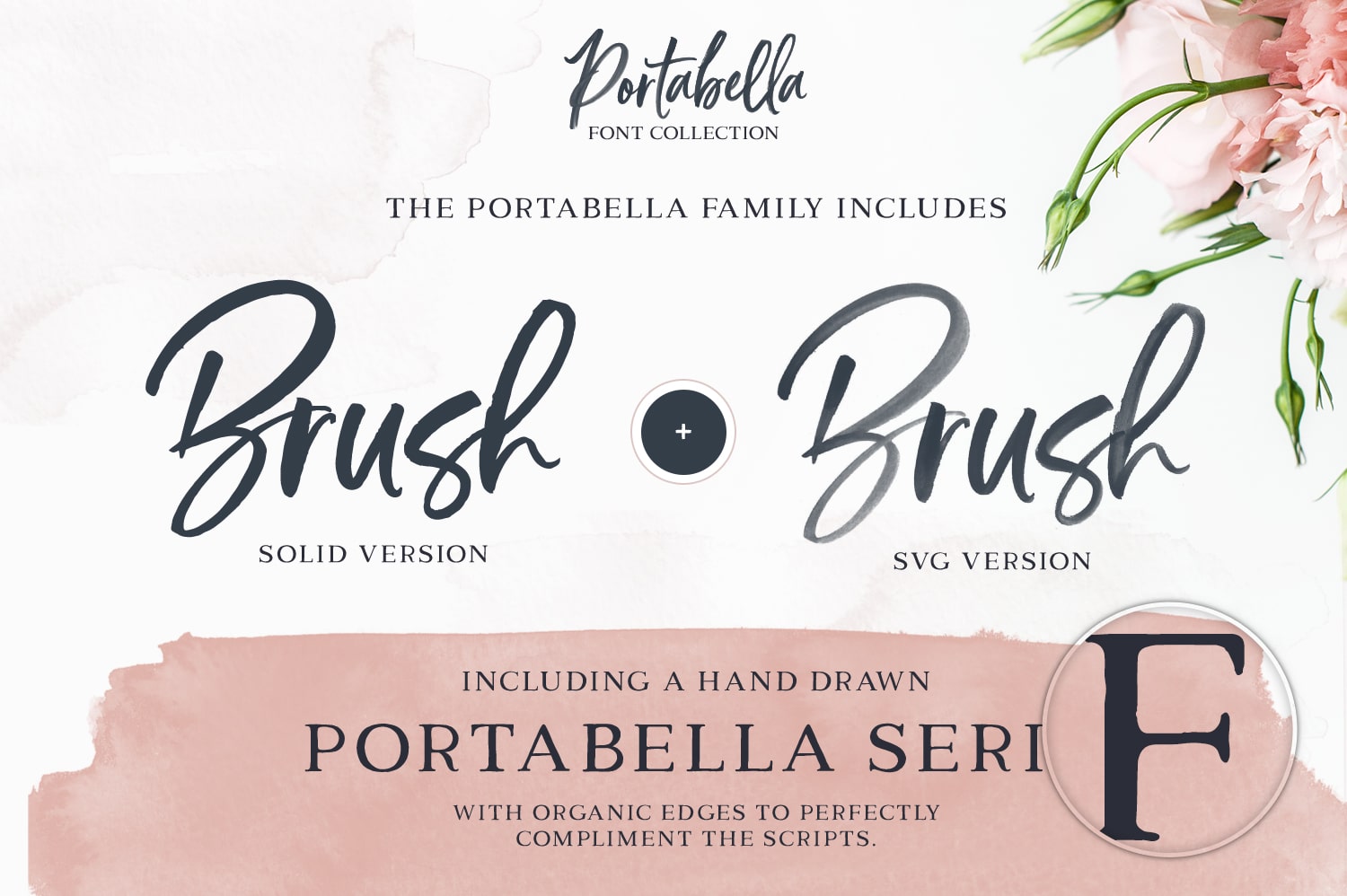
DESIGNCUTS(デザインカッツ)で、新しいバンドルが発売されました!
今回のバンドルは「デザイナーが愛用したい 極上フォントコレクション」。
「デザイナーが愛用したい 極上フォントコレクション」の気になる中身
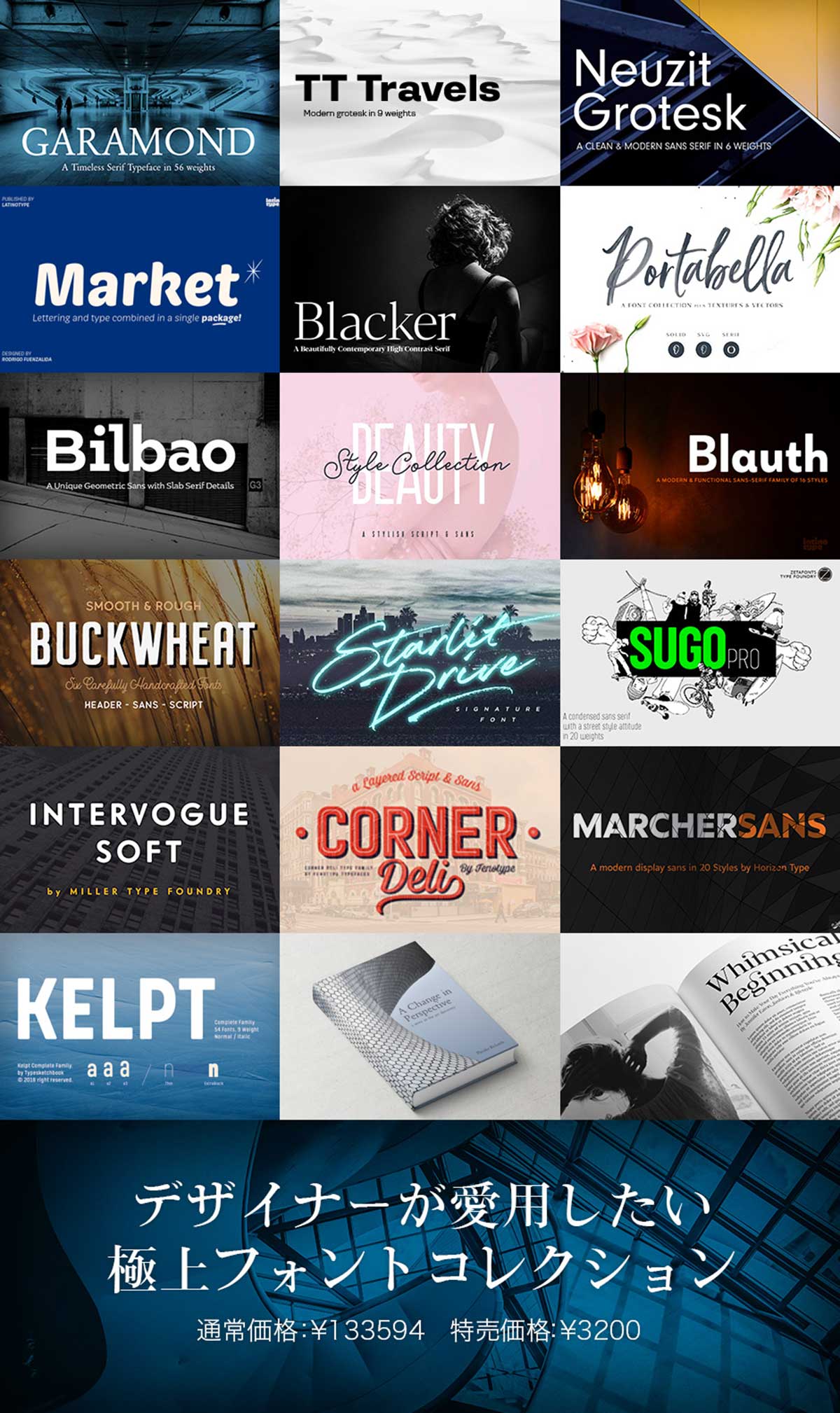
▼わたしが今回のバンドルで特に気になる素材はこちら!
持っておいて損なし!定番フォント:GARAMOND
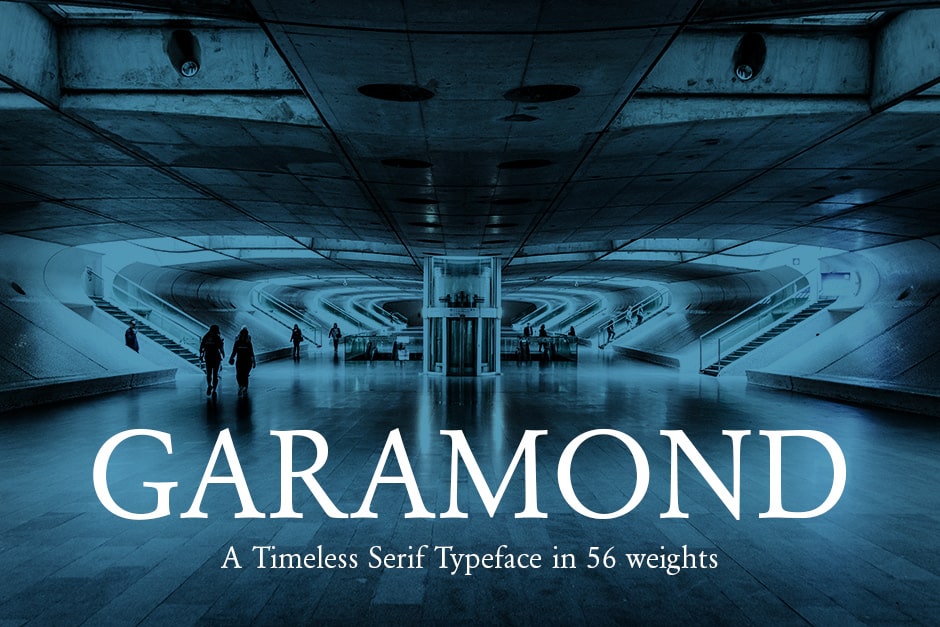
Claude Garamondによる伝説のフォントがなんと56ウェイトも収録。わたしも個人的に仕事でよく使っています。エレガントで読みやすく長文にも使えるので、ついつい選んでしまうフォントです。
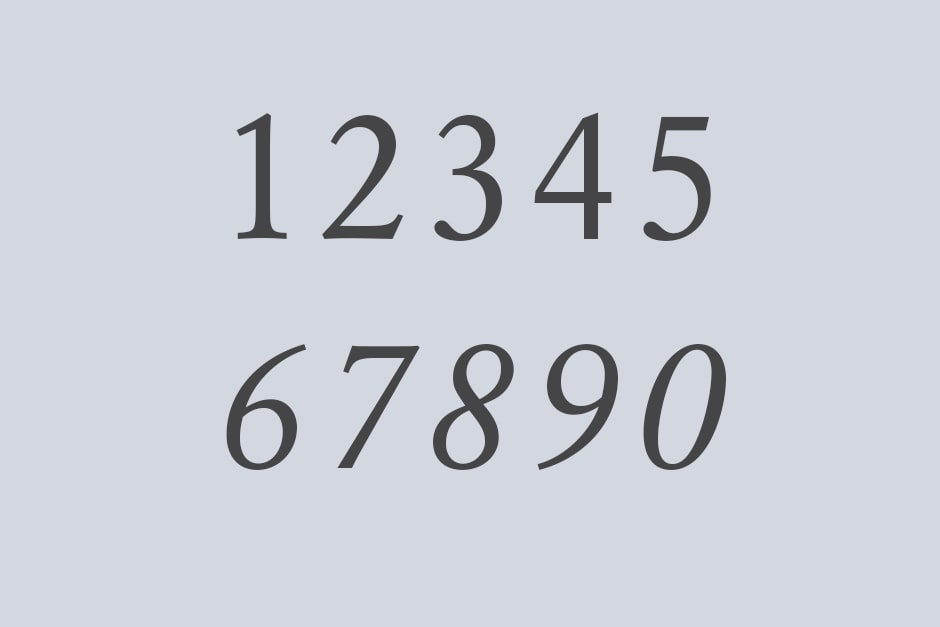
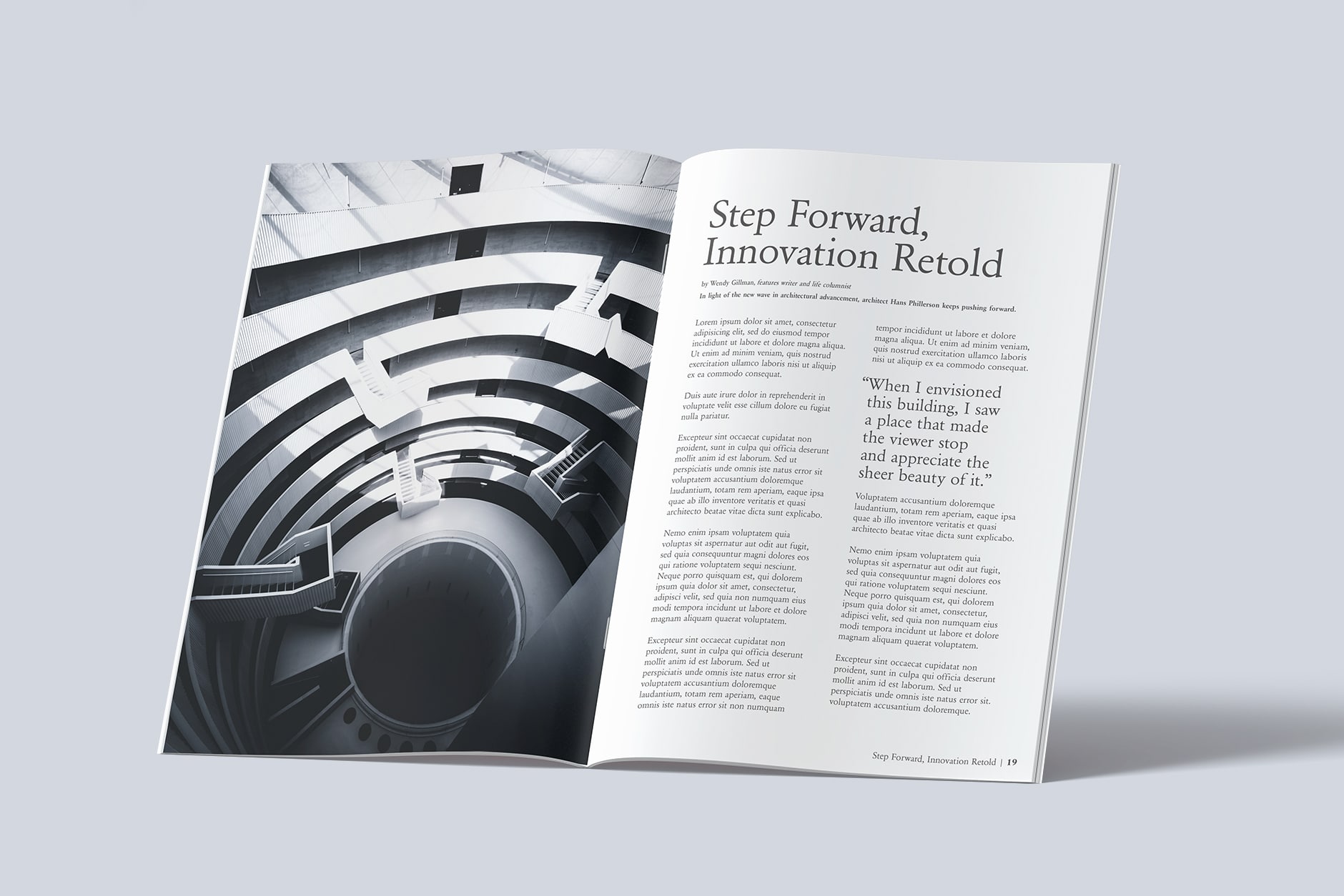
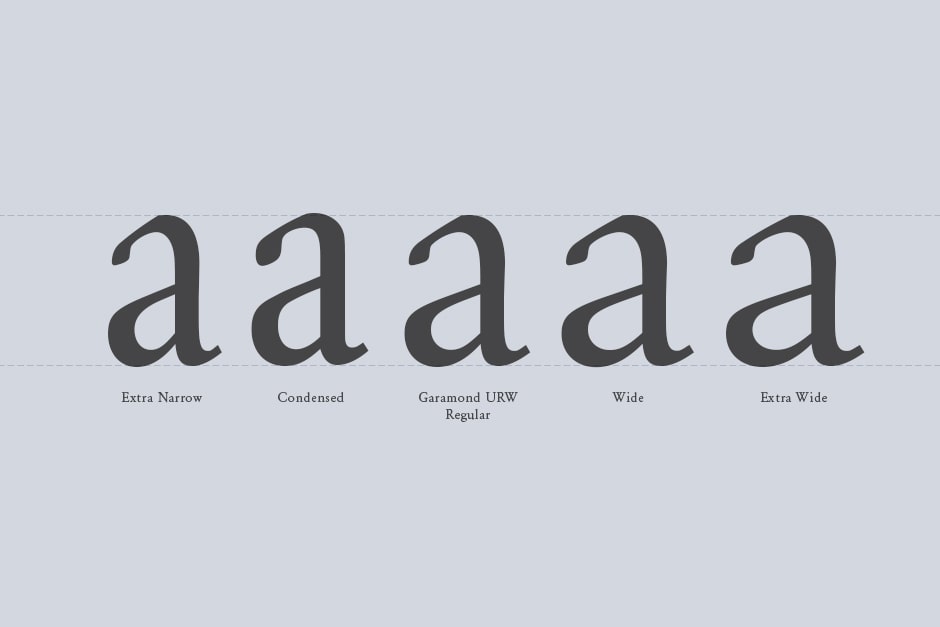
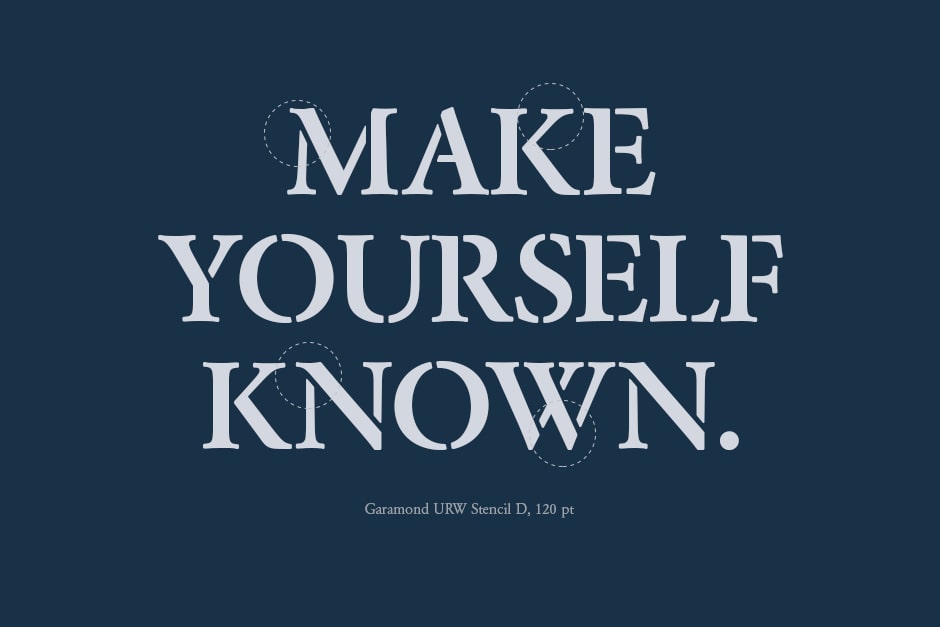
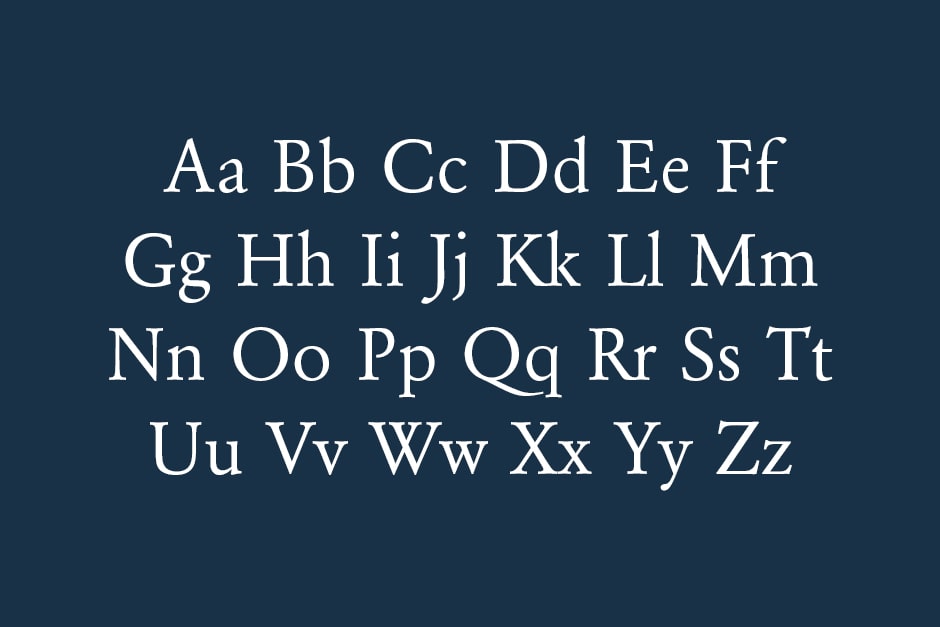
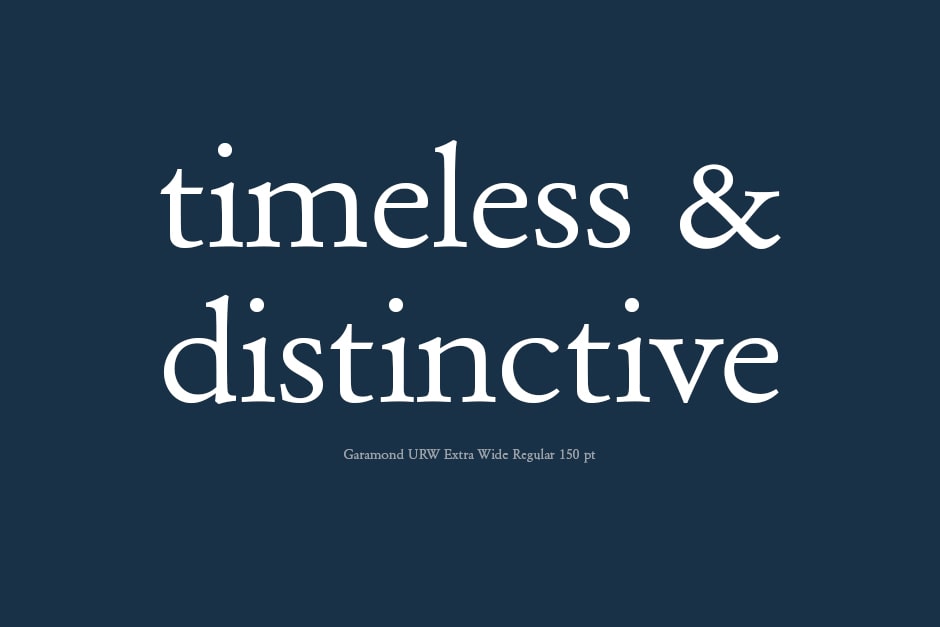
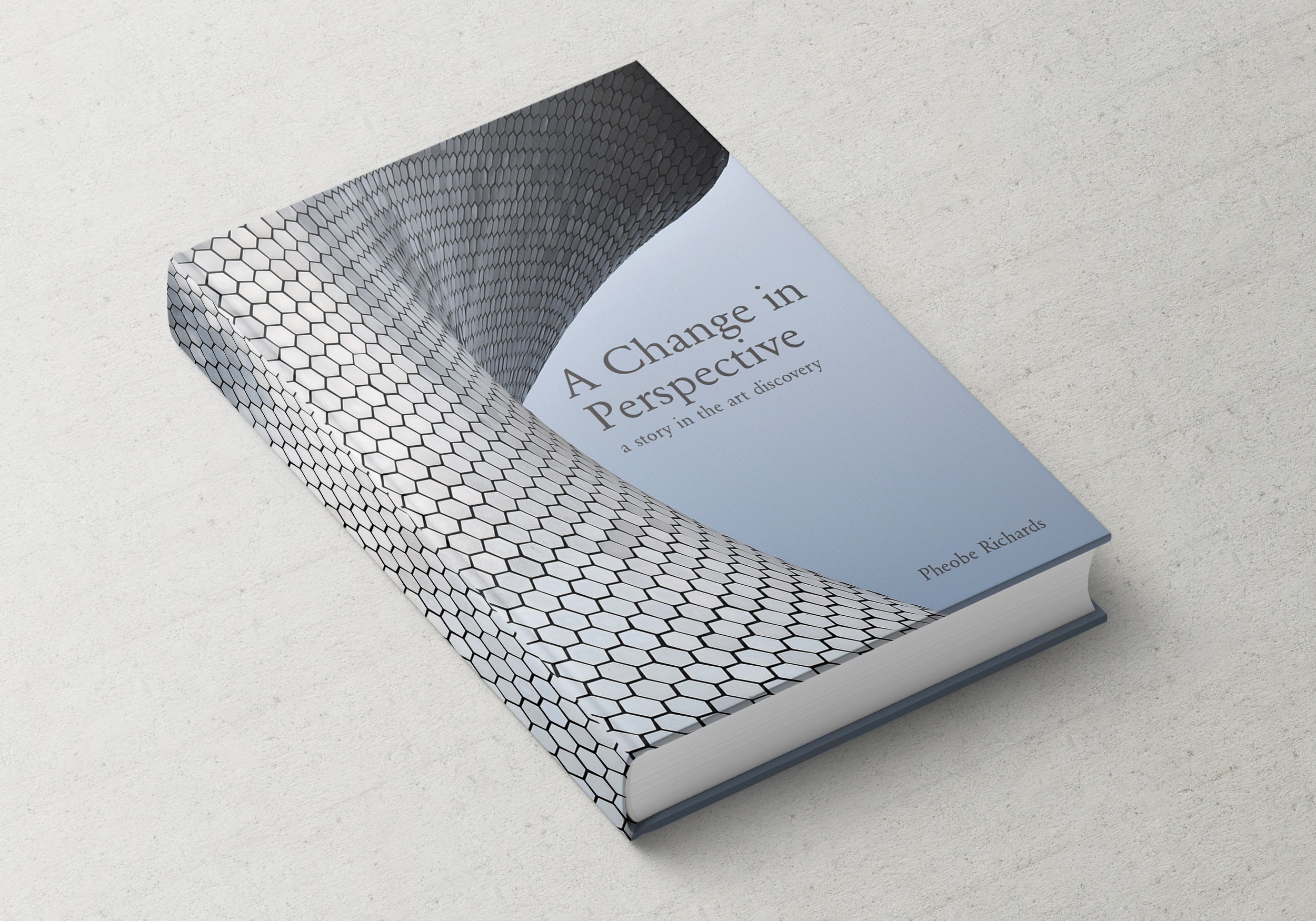
SVGフォントもついてくる筆記体フォント:PORTABELLA FONT COLLECTION
これを使うだけで、デザインが一気にドラマチックな雰囲気に変身するフォントセット。一緒に使う素材もセットになっていてお得!女性向けの媒体をデザインするときに活躍すること間違いなしです。